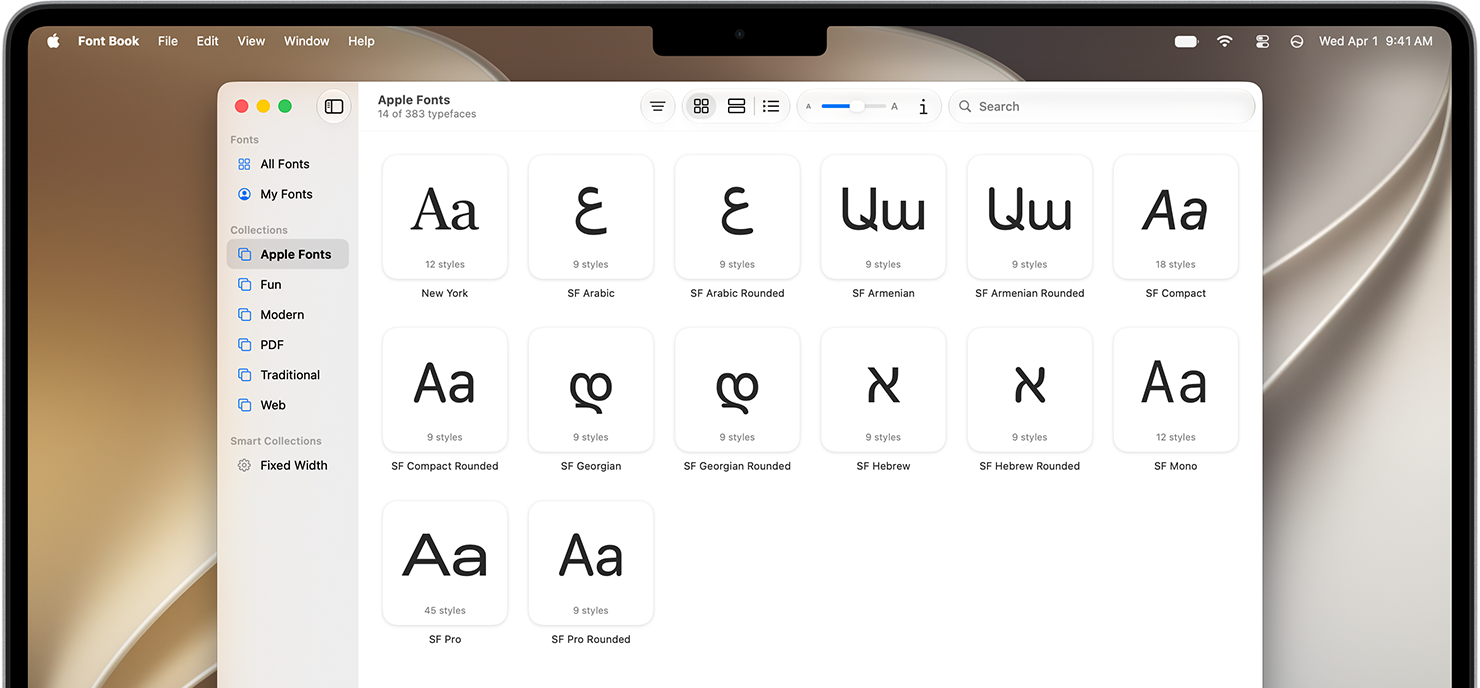
San Francisco
San FranciscoはAppleがデザインした書体で、一貫性があり、読みやすく、親しみやすい印象を与えるフォントです。すべてのApple製品において、文字サイズごとに最適化された字形と動的トラッキングにより、どのようなポイントサイズや画面解像度でも読みやすさが保たれます。数字はデフォルトでプロポーショナル幅になっており、日常的に使用する時間やデータの表示画面でも、調和のとれた自然な間隔で表示されます。
イタリック体を含む9ウェイトに加え、スモールキャップ、分数、上付き・下付き数字、添字、矢印などの機能があり、精密な文字組みに対応する幅広い表現力を備えています。またSan Franciscoは、さまざまな文脈にインテリジェントに適応します。例えば時間を表示する場合、San Franciscoのコロンは数字の縦幅の中央に揃う形に切り替わります。また、各オペレーティングシステムはこの書体と連携して、文字サイズに応じたフォント機能を自動的に適用します。
SF Pro
この中立的で汎用性の高いサンセリフ書体は、Appleプラットフォームのシステムフォントです。SF Proは、9ウェイト、読みやすさを最適化する可変オプティカルサイズ、4種類の幅、さらに丸みを帯びたバリアントを備えています。SF Proはラテン文字、ギリシャ文字、キリル文字による150以上の言語に対応しています。
SF Compact
SF Proと多くの機能を共有するSF Compactは、小さい文字サイズや幅の狭いカラム向けに最適化された、効率的でコンパクトなデザインを特長としています。SF CompactはwatchOSのシステムフォントであり、丸みを帯びたバリアントもあります。
SF Mono
テキストの行と列がきれいに揃う、San Franciscoの等幅バリアントです。Xcodeなどのコーディング環境で使用されます。SF Monoは6つのウェイトを備え、ラテン文字、ギリシャ文字、キリル文字に対応しています。
New York
San Franciscoと対をなすこのセリフ書体は、歴史的な書体の本質的な特徴を基にデザインされています。New Yorkは6ウェイトを備え、ラテン文字、ギリシャ文字、キリル文字に対応しています。さまざまな可変オプティカルサイズにより、小さいサイズでは伝統的なテキスト用書体として、大きいサイズではグラフィカルなディスプレイ用書体として最適に機能します。
SF書体のスクリプト拡張版
これらのAppleシステムフォント拡張版は、San Franciscoと同様、9つのウェイト、丸みを帯びたバリアント、そしてポイントサイズに応じて自動的に文字間隔とプロポーションが調整される可変オプティカルサイズを備えています。
各スクリプト拡張版は、多言語のタイプセッティングにおいてSF Proと調和しつつ、太さ、コントラスト、縦方向のメトリクスを調整することで、それぞれのスクリプト固有の自然な比率を保つようにデザインされています。
SF Arabic
Naskhスタイルを現代的に解釈した、合理的で柔軟なデザインを特徴とする書体。
SF Armenian
多言語のタイプセッティングにおいて視覚的なバランスが取れるように縦横比が調整されたデザイン。
SF Georgian
現代ジョージア語、ムヘドルリ文字、ムタヴルリ体の大文字の書式に対応。
SF Hebrew
ニクードの母音記号に完全に対応。
タイポグラフィの原則と、それがSan Franciscoフォントにどう適用されているかをご紹介します。San Franciscoフォントは、デザインチームとエンジニアリングチームの緊密な協働の成果と言えます。この書体は、表示する内容を優先することで、テキストに比類のない読みやすさ、明瞭さ、一貫性を与えます。